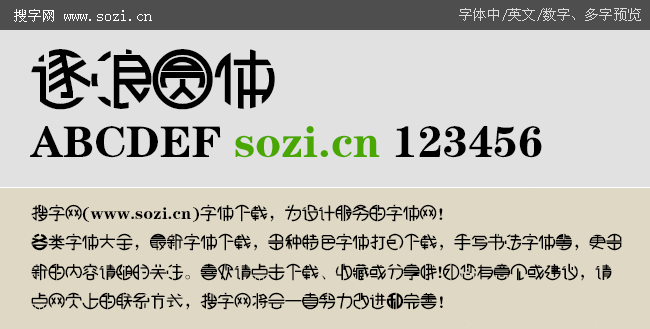
逐浪圓體
搜字網(wǎng)提供一款逐浪圓體中文字體下載,逐浪圓體是一款個(gè)性化POP字體,該字體非常具有趣味性,適合應(yīng)用于廣告設(shè)計(jì)、海報(bào)設(shè)計(jì)、POP設(shè)計(jì)等應(yīng)用。(逐浪字庫如需商用授權(quán),請(qǐng)聯(lián)系:0791-86161900 QQ:404655890)